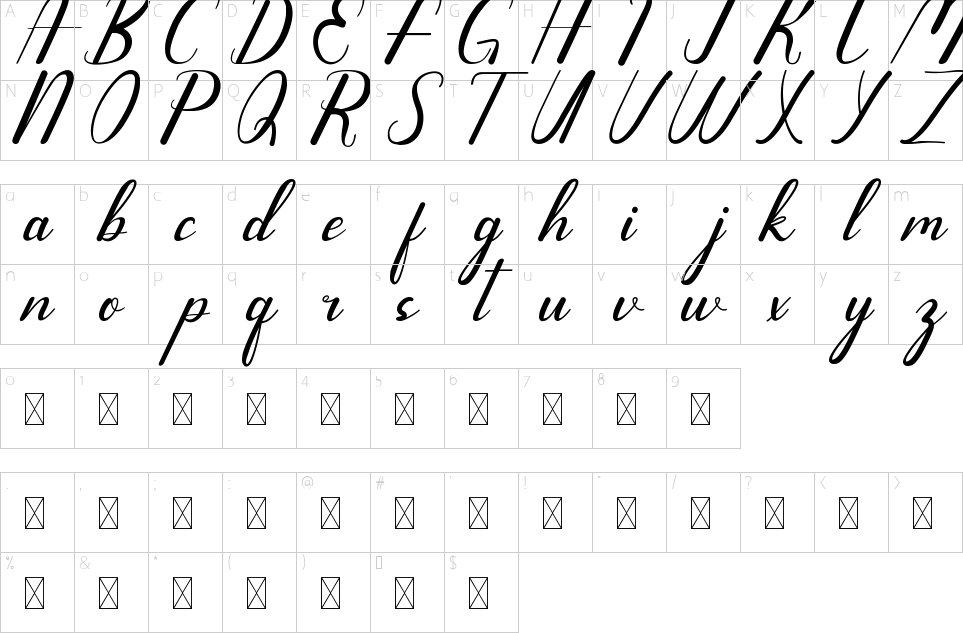
Descubra a Antropological Font, uma fonte originalmente criada pela designer noahtype. Essa fonte única e versátil foi projetada para oferecer um toque único e distintivo a qualquer projeto de design, seja para logotipos, e-books ou até mesmo para escrita cotidiana. Com uma gama de estilos distintos, a Antropological é ideal para quem busca diversidade e personalidade em suas criações. Não há mais motivo para limitar seu design a estilos convencionais quando a Antropological oferece uma paleta de opções que vai desde linhas geométricas até abstrações naturais, garantindo uma experiência de escrita e leitura agradável. Descubra por que essa fonte vem sendo amada por designers de todo o mundo, escolhendo a Antropological para dar um toque especial a seus trabalhos. Através da Antropological, você pode explorar a beleza intrínseca da cultura humana em sua própria forma única de expressão.